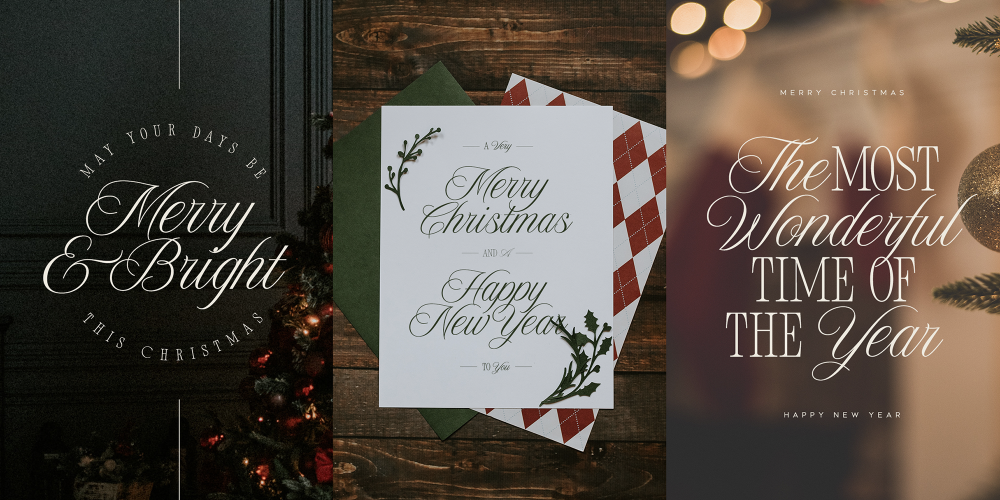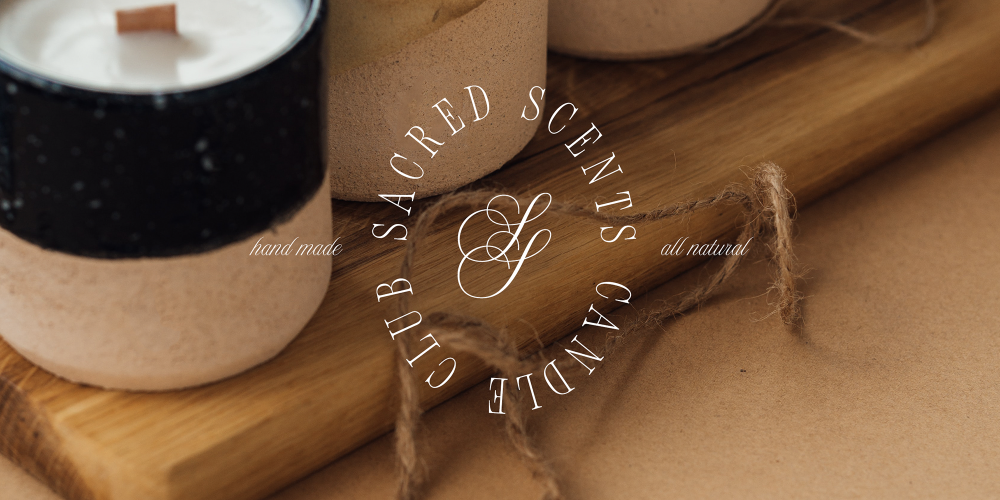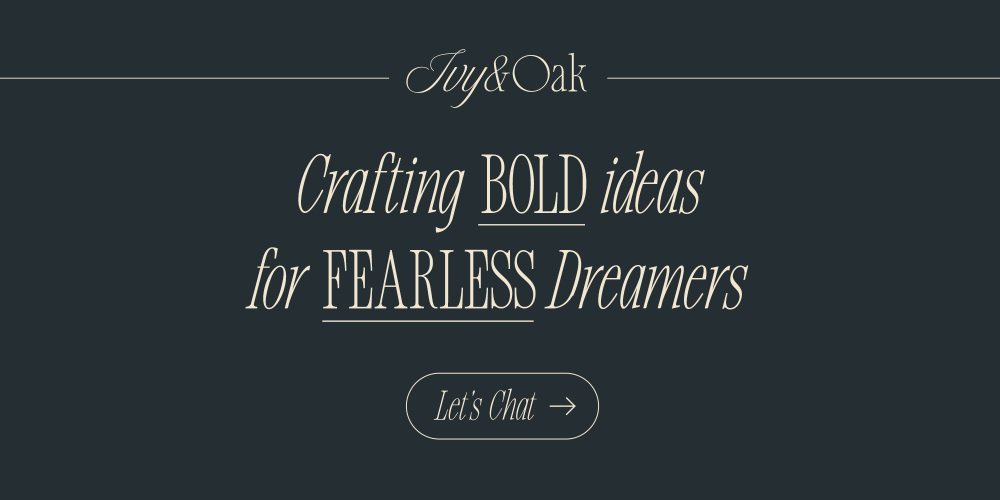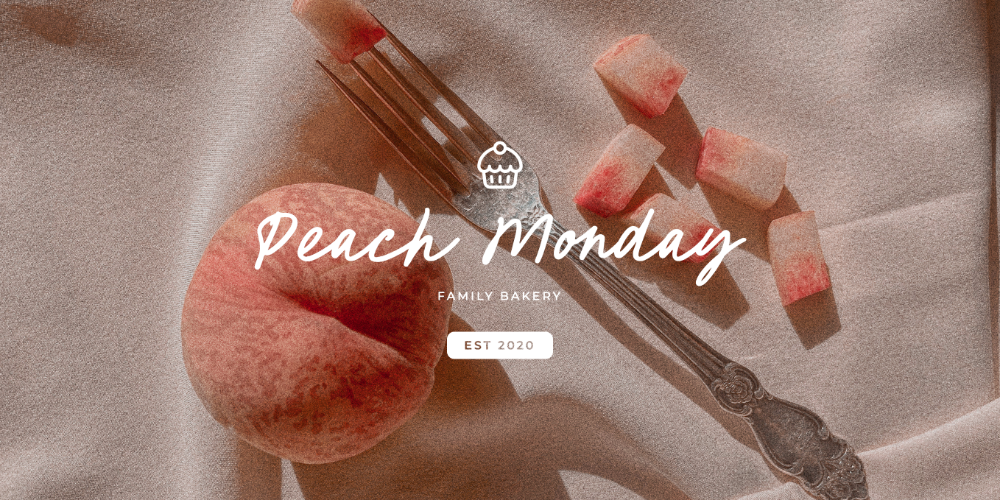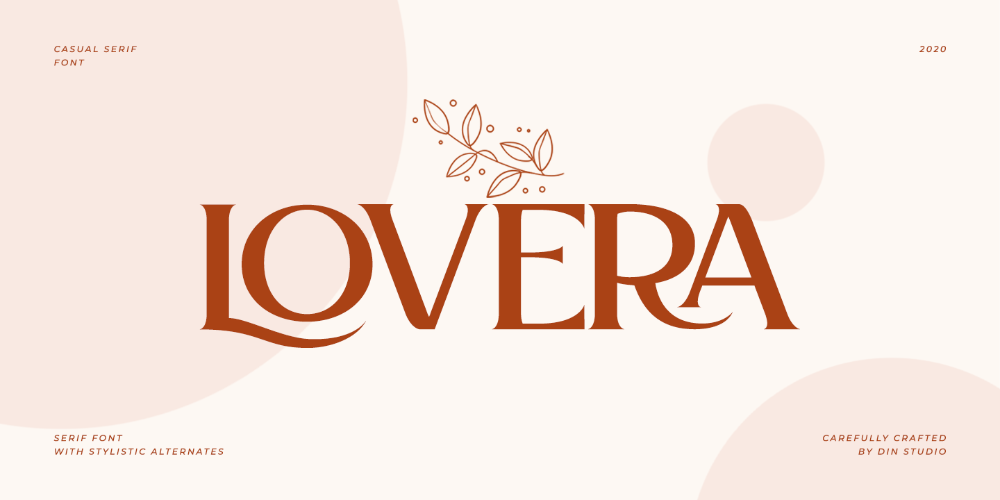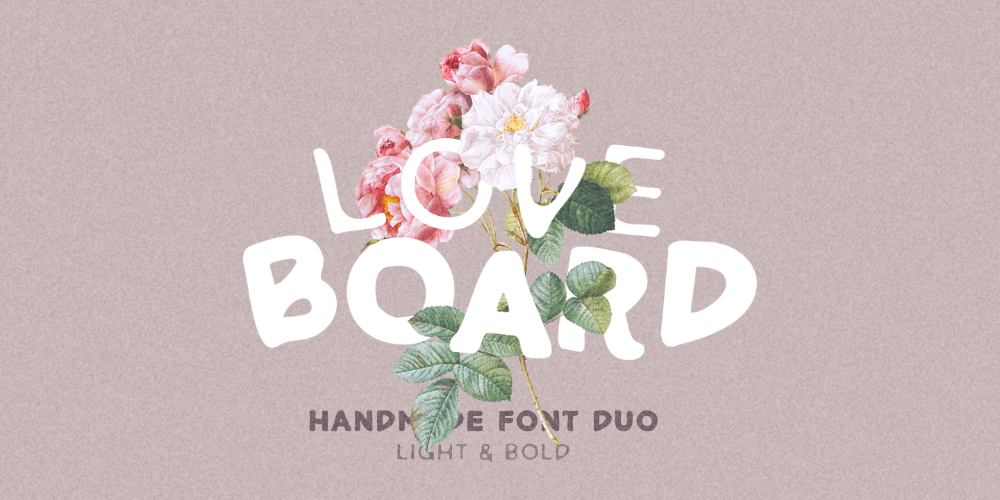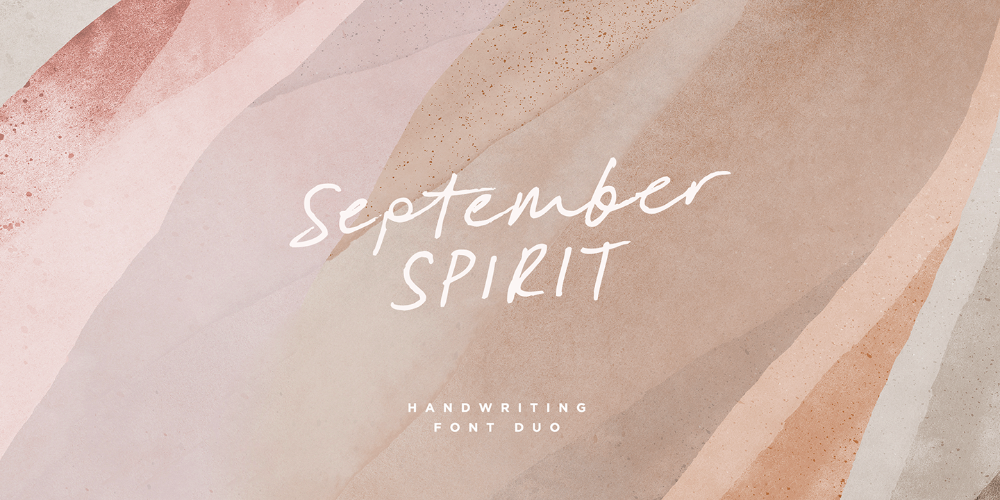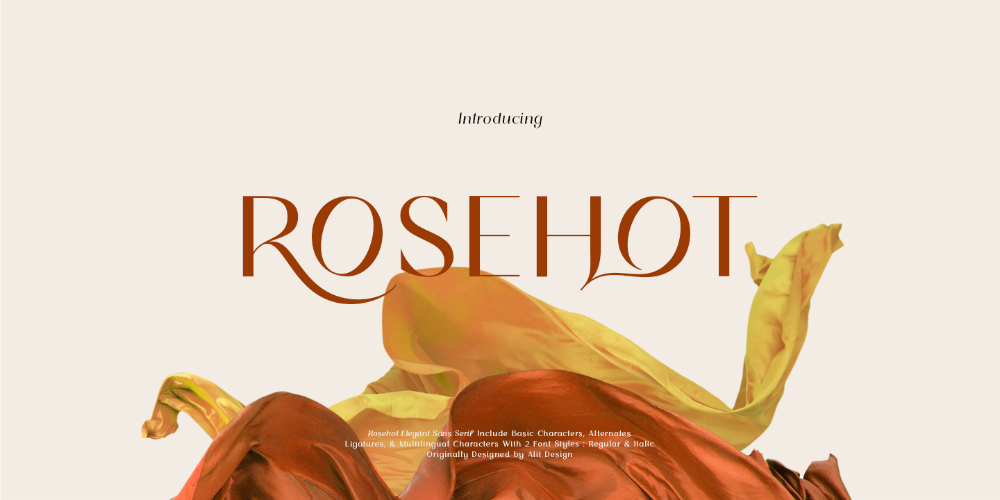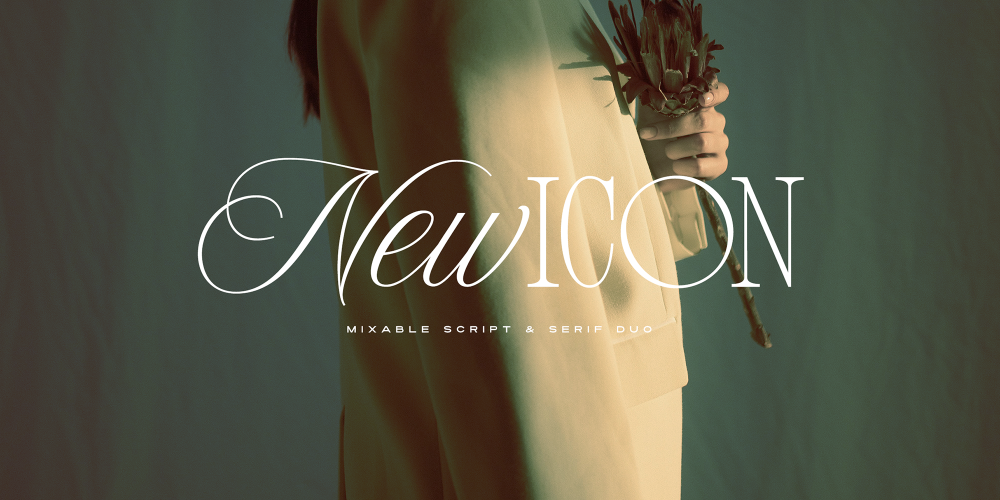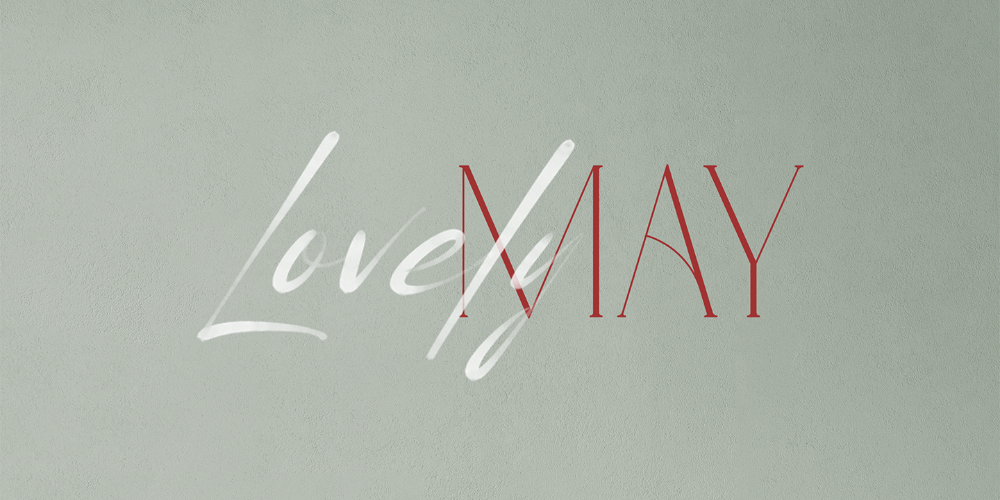
爱有无数种表达方式,或轻盈克制,或浓郁热烈。
在这个专属浪漫的七夕,设计也需要一份「情绪密码」。除了色彩与文案,一款恰到好处的字体,往往能让设计拥有更细腻的温度与氛围。
我们精选了 10 款别具温柔触感的字体,一同用字形细节,传递此时此刻的浪漫爱意。
细节一:高对比度衬线
粗细对比更为强烈的衬线体,自带现代都市的优雅氛围。纤细笔画仿佛情绪线索,收放之间,呈现克制又高级的浪漫感。
1|Walbaum
Foundry:Monotype
Walbaum 最初设计于 19 世纪早期,尽管它优雅大方、精致典雅,却从未获得过应有的关注和赞誉。现在,在这个庞大的字体家族中,它得到了全面的修复,包括 32 款字体,涵盖装饰元素和 2 款「特别款」。相比于 Bodoni、Didot 等传统衬线字体,Walbaum 别具温馨感,让人感觉轻松易认。
蒙纳团队 Carl Crossgrove、Charles Nix 和 Juan Villanueva 秉承了设计师 Justus Erich Walbaum 的设计初衷,同时还将设计师儿子的作品融入了一些更为夸张的标题字重中,在不影响其设计灵魂的前提下,推动了 Walbaum 字体的发展。
2|Lovera
Foundry:Din Studio
Lovera 是一款优雅的高对比度衬线字体,专为各种专业品牌项目而设计。其笔画粗细对比鲜明,带来强烈的节奏感与视觉层次,让字体在保持优雅气质的同时更具设计张力。
每一个字母都带有精巧而美丽的细节,配合优美的连字设计,呈现出极具装饰感的字体美学,同时支持多语言、数字与标点符号。
3|Lovely May
Foundry:VP Creative Shop
Lovely May 是一款优雅且充满自然气息的多字体组合。衬线体笔画粗细对比鲜明,带来强烈的视觉节奏感;手写体则轻盈流畅,仿佛不经意的随手一笔,却透露出温柔与浪漫。
字体在大字号标题与小字号正文中均表现出色,适用于品牌设计、家居产品包装、杂志标题、海报文案等多元场景,也可作为背景图片上的精致文字点缀。
细节二:手写体
手写体的独特魅力在于它的流畅笔触与自由线条,带着近乎随性的一笔一划,却能传递出浓烈的情感温度,设计在保持优雅的同时多了一份亲近与真实。
4|Marylebone
Foundry:Los Andes
Marylebone 是一款以伦敦同名街区为灵感的字体,专为咖啡馆、书店、花店及本地小店的广告、黑板文字和橱窗短文而设计。手写刷笔体笔触自然流畅、线条略带弧度与粗细变化,呈现随性却精致的书写风格。
5|Blackberry Macarons
Foundry:PeachCreme
Blackberry Macarons 是一套甜美俏皮的三字体组合,包含优雅装饰体、浪漫手写体和手绘无衬线体。
装饰体带有精致延伸笔画,手写体流畅自然,连字丰富,而无衬线体略带不规则的手绘感,为设计增添温度与趣味,非常适合包装、贺卡、插画和标题设计。
6|Des Montilles
Foundry:Supfonts
Des Montilles 是一款随性自然的手写字体,笔触轻盈流畅,带有手写连字、首尾延伸和心形连接设计,增添浪漫细节。
7|September Spirit
Foundry:Set Sail Studios
September Spirit 是一款流畅自然的手写字体,笔触轻快自然,字形富有呼吸感,呈现随性优雅的气质。
套装还包含替代字形、全大写版本以及手绘箭头、圈线等装饰元素,为排版增添更多手写创意细节。
细节三:花笔
花笔细节指的是字体笔画末端带有的装饰性延伸或弧线,常见于手写体和浪漫风格字体中。这些优雅的弯曲、延展和装饰笔触让字形更具流动感与表现力,为设计增添轻盈浪漫的氛围。
8|New Icon
Foundry:Set Sail Studios
New Icon 是一组优雅的双字体组合,包含奢华手写体与经典衬线体。
手写体以传统书法为灵感,笔画流畅,带有精致的花字细节,末端延伸出自然优雅的氛围;衬线体简洁大气,与手写体搭配能形成富有表现力的排版效果。
9|Rosehot
Foundry:Alit Design
Rosehot 笔画流畅自然,曲线柔美,字形细节光滑精致。其花笔的延伸设计为每个字母增添装饰性弧线和优雅曲线,使文字在视觉上更具流动感和浪漫气息。
无论用于标题、婚礼请柬、品牌设计还是文艺风格的排版,都能为作品带来温柔灵动之感。
细节四:油墨陷印
油墨陷印是字体笔画交汇处或转角的微小凹陷设计,本用于提升印刷清晰度,但意想不到的是,如果运用恰当,这种细微的凹陷让字形更为柔和,增添温润的层次感。
10|Love Board
Foundry:Sarid Ezra
Love Board 是一款手作风格的无衬线体,笔触自然,带有人文手写感。字体在笔画转角处巧妙运用了油墨陷印设计,使每个字母更有呼吸感和立体感。
两种互补字重也让它在书籍封面、包装设计等多种创意场景中都能展现自然亲切的氛围。
"title": "七夕浪漫字体特辑|花笔、手写、油墨陷印……这些细节让字体更具细腻情感"